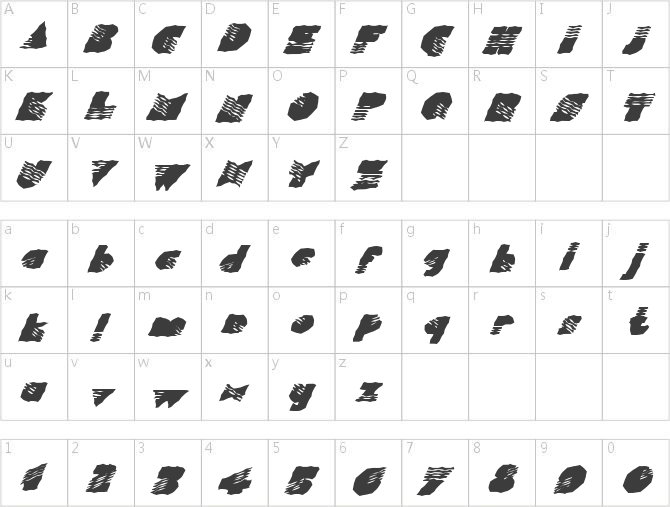
FZ WACKY 40 ITALIC 詳情頁(yè)
FZ WACKY 40 ITALIC字體字庫(kù)是一款讓人賞心悅目、百看不厭的英文字體,適合各類(lèi)廣告和產(chǎn)品包裝設(shè)計(jì)應(yīng)用,字體大小0.08MB,格式為ttf字體,上傳用戶(hù)是shiqiuping,作者/版權(quán)方為未知